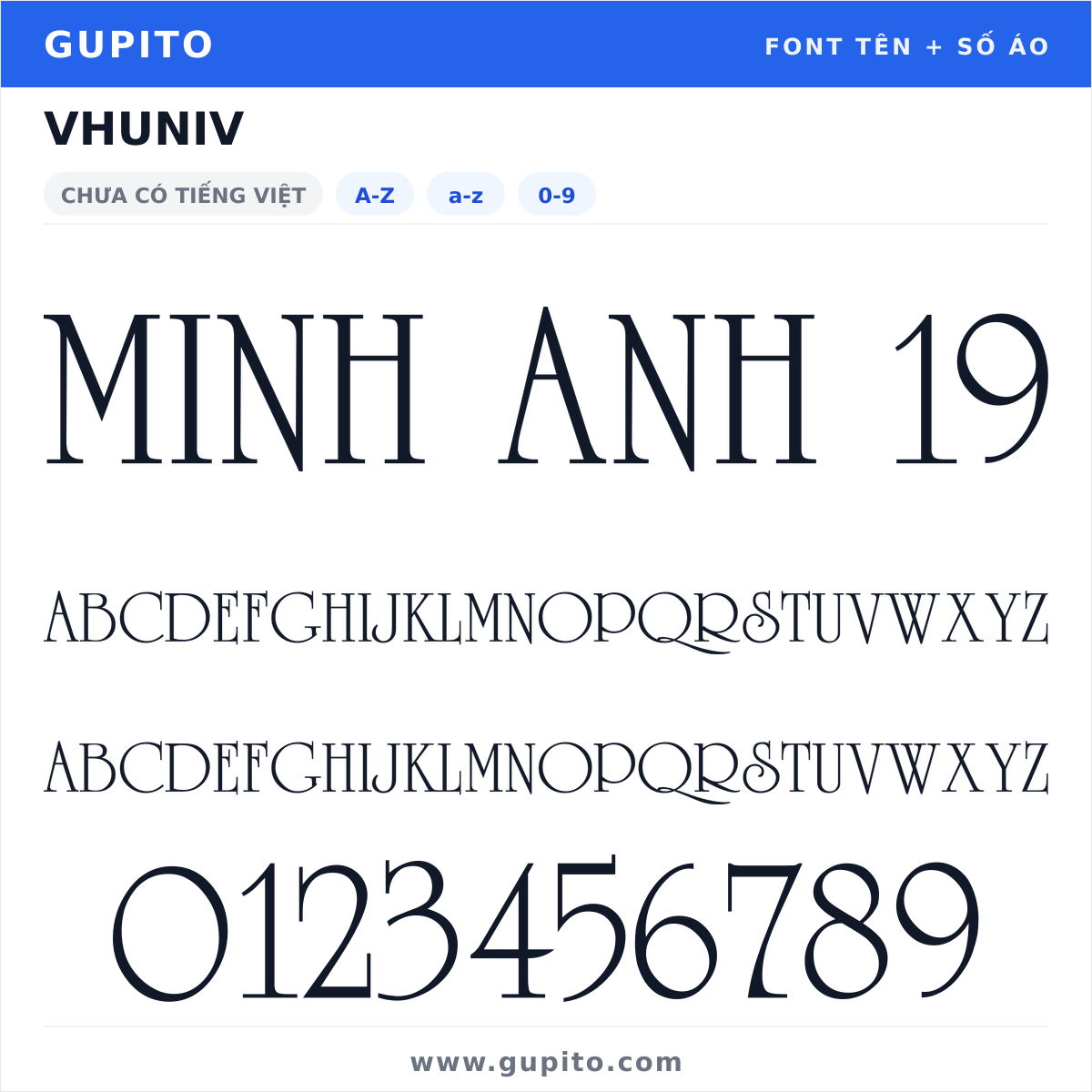
.VnUniverseH Normal
.VnUniverseH Normal · Font VHUNIV in tên áo số, font chữ thể thao, font in chuyển nhiệt · thanh lịch, thể thao
Font VHUNIV với nét chữ thanh lịch, có bảng số 0-9, phù hợp in tên áo bóng đá, áo lớp, quà tặng. Font in chuyển nhiệt chất lượng cao. Bộ chữ .VnUniverseH Normal dùng để in chuyển nhiệt lên áo đấu, áo lớp, áo nhóm và đồ thể thao theo yêu cầu. Kiểu dáng: thanh lịch, thể thao. Font dùng cho chữ không dấu và số áo. Có đủ bộ chữ số để in số áo. Từ khoá liên quan: font vhuniv, font in ten ao, font in so ao, font ao bong da, font the thao, font in chuyen nhiet, font co bang so, font chu hoa.